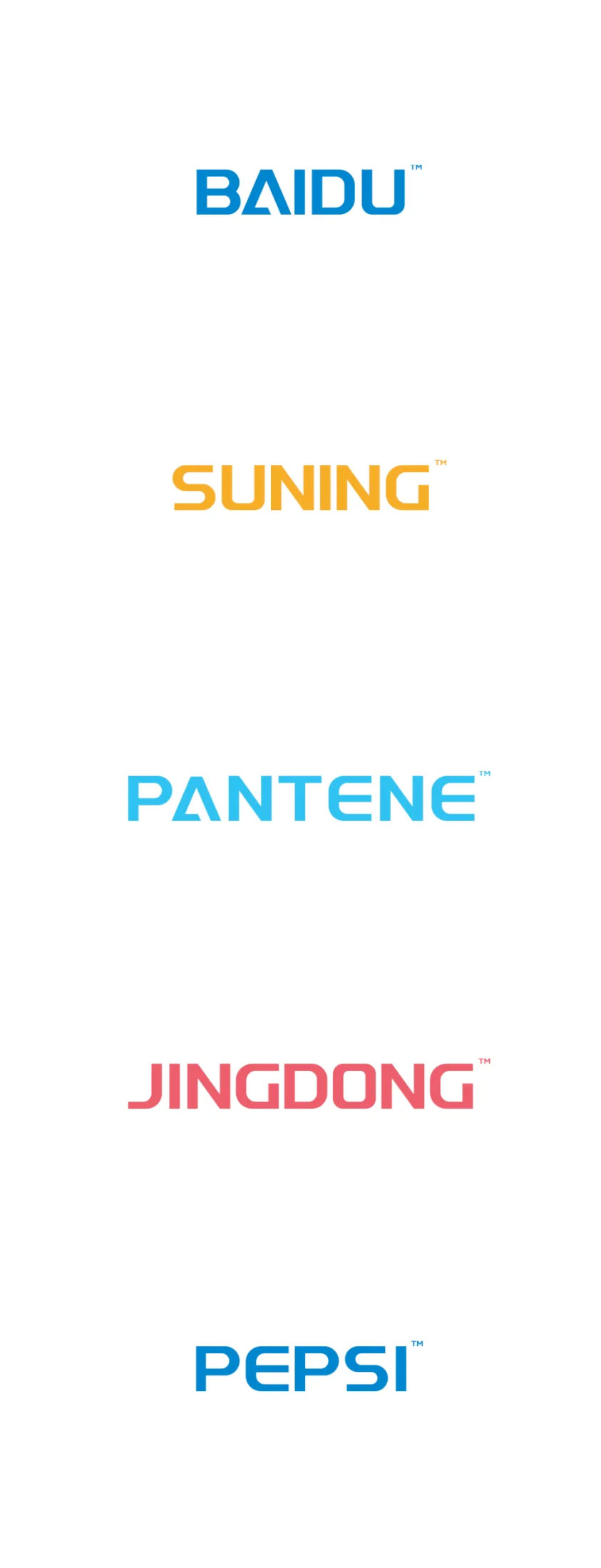
字体圈欣意LOGO体
字体圈欣意LOGO体字体介绍
字体圈欣意LOGO体是国内字体设计师邹乐伟创作的一套英文字库,适用于标题、LOGO设计等场合使用,目前包含52个英文10个数字和几个标点。
该字体无论是互联网公司,还是服装品牌,还是玩具公司,还是食品公司,还是大型企业等等,都是很适合的!
字体圈欣意LOGO体字体应用示例